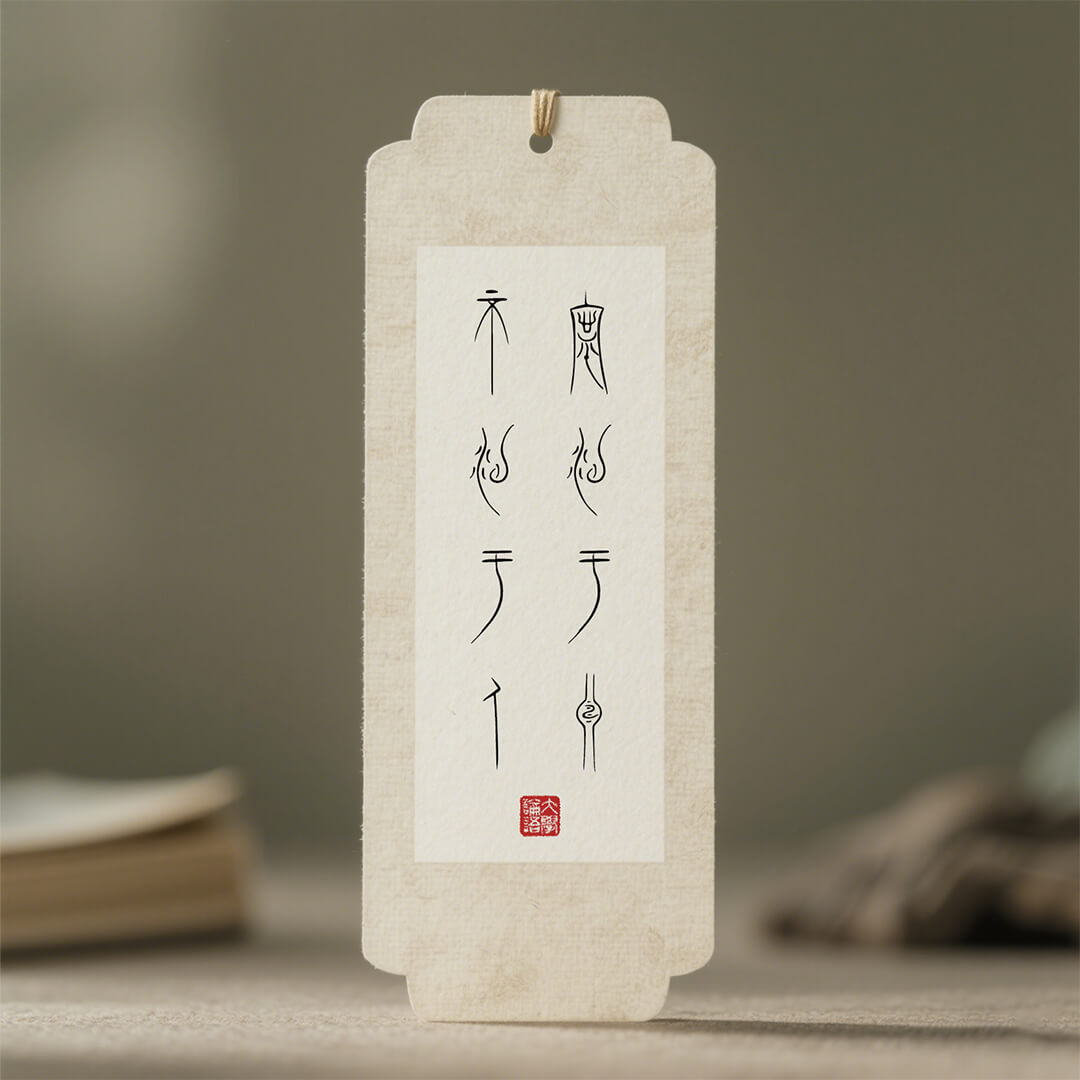
"敬峰中山王篆"(Seal Script of the Zhongshan Kingdom, Jingfeng style)是一款基于战国时期中山国青铜器铭文风格开发的数字篆书字体。本字体由刘敬峰先生创作,力求在忠实还原历史风格的基础上进行合理的字形补充与数字化呈现。
简介
本字体以"中山三器"铭文为主要原型,结合战国文字体系、甲骨文、金文等早期书写传统,对缺失字形进行了合理推演与设计补充,最大程度地再现古代篆书之美。
- v1.0 版本包含约 1600 个汉字
- 收录"中山三器"中最具代表性的优美字形
- 扩展至《道德经·帛书本》全文单字
- 未来将持续完善字库,提升覆盖度与表现力
- v2.0 版本包含约 2300 个汉字
- 收录"中山三器"中最具代表性的优美字形
- 字库升级至 2327个字符,大约2300个中山王篆单字,内容覆盖《道德经帛书版》、《人教版小学必背古诗》。每个新字基本都有原铭文的痕迹,就像煮新卤水要加点老卤水一样,让中山王篆的古韵不断传承。
- 修正第一版的部分错别字。
当前支持内容
- 中山三器代表性字形(约300字)
- 《道德经·帛书本》全文单字(约1600字)
- 《人教版小学必背古诗》